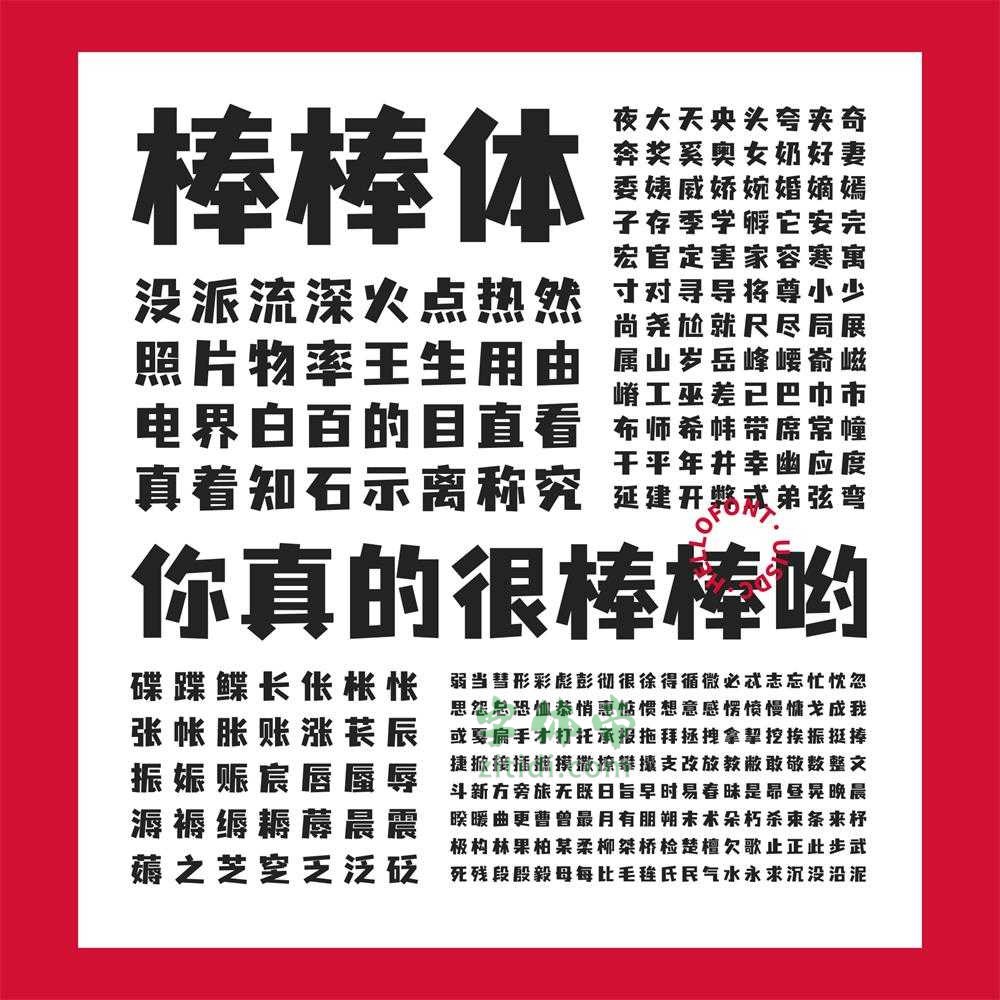
优设字由棒棒体的名称是字由提议的三个方向选择而来,初始的三个版本是棒棒体、CP 体、联合体,最终经过讨论确定为棒棒体。一方面是寓意 2021 年工作棒棒,身体棒棒,新年棒棒。另一方面,由于字体本身的结构比较像棍子组成的笔划,棒棒体听起来也有一种轻松可爱的感觉,和字体的整体感觉比较相符。
“优设字由棒棒体”是一款书写很新颖的字体,字体大方,适合各种设计作品使用!欢迎下载!